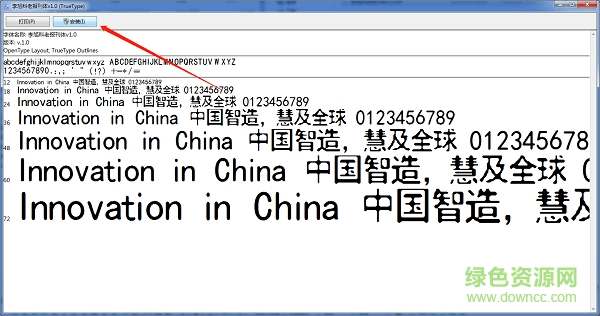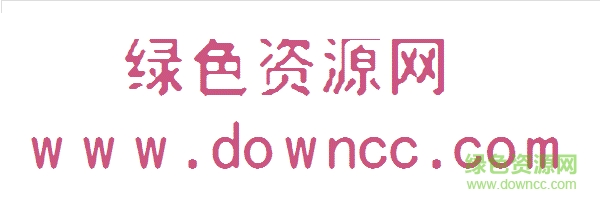
李旭科老報(bào)刊體是一款富有藝術(shù)氣息的中文簡(jiǎn)體字體,字體取材于老報(bào)刊的素材,將簡(jiǎn)單的富有年代氣息的特色融入到字體之中,用戶使用此款字體排版別有一番回味的感覺,喜歡就來(lái)綠色資源網(wǎng)下載吧!
李旭科老報(bào)刊體是一款由李旭科設(shè)計(jì)制作的中文簡(jiǎn)體藝術(shù)字體,字如其名,就像是老報(bào)紙上的字體一樣,給人一種經(jīng)典懷舊的感覺,比較適合用作印刷品制作、雜志封面、平面設(shè)計(jì)素材等使用,能夠支持簡(jiǎn)體漢字、英文字母、數(shù)字符號(hào)等多種字體格式,滿足日常使用!